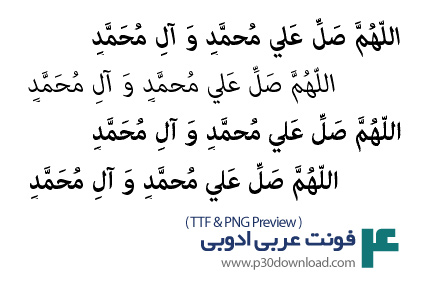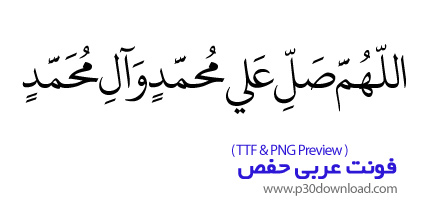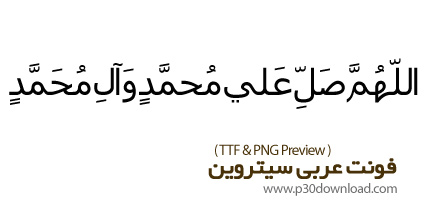
دانلود Meshkal Arabic Font - فونت عربی مشکال: / در این بخش شاهد فونت عربی مشکال می باشید که با فرمت OTF بر روی سایت برای دانلود قرار گرفته است. Meshkal یک فونت نمایشی (Display Font) عربی با طراحی منحصربه‌فرد و مدرن است که از الگوها و ساختارهای هندسی کالیدوسکوپی (Kaleidoscopic Geometries) الهام گرفته شده است. نام این فونت از واژه عربی «مشکال» به معنای کالیدوسکوپ گرفته شده و به‌خوبی بازتاب‌دهنده سبک هندسی و چشم‌نواز آن است. این فونت با ساختاری مستحکم، خطوط ضخیم و لبه‌های تیز طراحی شده و برای پروژه‌هایی که نیاز به تایپوگرافی شاخص، مدرن و متفاوت دارند، گزینه‌ای ایده‌آل محسوب می‌شود. طراحی خاص Meshkal باعث می‌شود در عناوین، پوسترها، برندینگ و پروژه‌های گرافیکی جلوه‌ای قدرتمند و متمایز ایجاد کند. اگر به دنبال یک فونت عربی با هویت هندسی، مدرن و متفاوت هستید، Meshkal Arabic Font با الهام از ساختارهای کالیدوسکوپی و طراحی قدرتمند خود می‌تواند انتخابی عالی برای پروژه‌های تایپوگرافی، پوستر، برندینگ و طراحی‌های خلاقانه باشد. ...
دانلود Bree Arabic 7 Styles Font Family - فونت عربی و انگلیسی بر با 7 استایل مختلف: / در این بخش شاهد فونت عربی و انگلیسی بر با 7 استایل مختلف می باشید که با فرمت های OTF و TTF و WOFF و WOFF2 و JPG بر روی سایت برای دانلود قرار گرفته است. Bree Arabic 7 Styles Font Family  یک خانواده فونت عربی/انگلیسی زیبا و حرفه‌ای است که با طراحی نرم، خوانا و مدرن، گزینه‌ای بسیار مناسب برای انواع پروژه‌های گرافیکی، تبلیغاتی، چاپی و دیجیتال به شمار می‌رود. این مجموعه معمولاً شامل  7 استایل مختلف  از فونت Bree Arabic است که به طراحان اجازه می‌دهد در عین حفظ یکپارچگی بصری، از وزن‌ها و حالت‌های متنوع برای تیتر، متن، لوگو، پوستر، رابط کاربری و محتوای تبلیغاتی استفاده کنند. اگر به دنبال فونتی هستید که هم  ظاهر امروزی و حرفه‌ای  داشته باشد و هم در زبان عربی و فارسی از خوانایی خوبی برخوردار باشد، این خانواده فونت می‌تواند انتخابی کاربردی و ارزشمند برای آرشیو طراحی شما باشد. Bree Arabic نسخه عربی/سازگار با اسکریپت عربی از خانواده فونت Bree است که با حفظ روح طراحی اصلی، برای نوشتار عربی و فارسی بهینه‌سازی شده است. فرم حروف در این فونت معمولاً ترکیبی از  نرمی، صمیمیت، شخصیت بصری مدرن و خوانایی بالا  است؛ به همین دلیل در پروژه‌هایی که هم زیبایی و هم وضوح متن اهمیت دارند، عملکرد بسیار خوبی دارد. ...
دانلود True Arabic Coorporate Clean Sans - فونت عربی و انگلیسی با طراحی مدرن: / این بخش شامل فونت True Arabic Coorporate Clean Sans با پشتیبانی از زبان‌های عربی و انگلیسی می‌باشد که با فرمت‌های OTF، TTF، WOFF و WOFF2 در سایت برای دانلود قرار گرفته است. این فونت مدرن و زیبا، انتخابی ایده‌آل برای طراحی‌های حرفه‌ای و معاصر است و با طراحی تمیز و خوانا، کاربرد گسترده‌ای در پروژه‌های دیجیتال و چاپی دارد. این فونت با ترکیب وضوح، دقت و زیبایی‌شناسی مدرن، یک ابزار حرفه‌ای برای طراحان است و امکان خلق طرح‌های مینیمال، جذاب و خوانا را در هر نوع پروژه فراهم می‌کند. ...
دانلود RAFRAF Font - دانلود فونت عربی و انگلیسی رفراف: / در این بخش شاهد فونت عربی و انگلیسی رفراف می باشید که با فرمت TTF بر روی سایت برای دانلود قرار گرفته است. فونتH RAFRAF یک فونت عربی مدرن و زیباست که با هدف ایجاد خوانایی بالا و طراحی چشم‌نواز ساخته شده است. این فونت صرفاً بر پایه حروف عربی طراحی شده و ممکن است نسخه‌ای ویژه بدون پشتیبانی از حروف لاتین (انگلیسی) باشد. رفراف یک فونت عربی با طراحی معاصر است که به خوبی می‌تواند در طراحی‌های حرفه‌ای مورد استفاده قرار گیرد. ...
دانلود RTL ManGo Arabic Typeface - فونت عربی مانچو: / RTL ManGo Arabic Typeface یک نوع فونت عربی با استفاده از حروف راست به چپ است. این فونت، برای نوشتن و طراحی در زبان عربی و متونی که در جهت راست به چپ نوشته می‌شوند، مناسب است. با استفاده از این نوع فونت، می‌توانید متونی را در استایل و ظاهر عربی منحصر به فردی طراحی و نمایش دهید. RTL ManGo Arabic Typeface انتخابی مناسب برای طراحان گرافیک، نویسندگان عربی و هر کسی است که به دنبال یک فونت عربی با استایل منحصر به فرد می‌باشد که با فرمت های OTF و TTF و JPG بر روی سایت برای دانلود قرار گرفته است. ...
دانلود Lenos Font Family - فونت فارسی، عربی و انگلیسی لینوس: / لنوس (Lenos) نسخه مدرنی از فونت عربی قدیمی "نسخ" است، یک فونت ارگانیک مدرن که سنس و "نسخ" را در یک خانواده قدرتمند با 9 وزن مختلف از نازک تا سیاه و تمام گزینه‌های مورب آن ترکیب می‌کند. لنوس بیش از 50 زبان مختلف را از جمله اردو، فارسی، اسپانیایی، ترکی و غیره، ترکیب می‌کند و همگی قابل استفاده در برنامه‌های دیجیتال و آفلاین هستند. این فونت زیبا با فرمت های OTF و TTF و PNG بر روی سایت برای دانلود قرار گرفته است. ...
دانلود Salford Sans Latin & Arabic Font Family - فونت لاتین و عربی صلفرد سانز: / در این بخش شاهد فونت لاتین و عربی صلفرد سانز می باشید که با فرمت OTF بر روی سایت برای دانلود قرار گرفته است. فونت Salford Sans Latin & Arabic Font Family یک خانواده‌ی تایپوگرافی مدرن و همه‌کاره است که به‌طور حرفه‌ای برای پوشش زبان‌های لاتین و عربی طراحی شده است. این خانواده فونت برای طراحانی ساخته شده که به دنبال هماهنگی کامل میان متون انگلیسی و عربی در پروژه‌های چندزبانه هستند. سبک‌های لاتین و عربی در این خانواده فونت به‌صورت کاملاً هماهنگ طراحی شده‌اند تا انسجام بصری در پروژه‌های چندزبانه ایجاد کنند. این فونت با تمرکز بر خوانایی و سادگی، مناسب برای استفاده در وب‌سایت‌ها، اپلیکیشن‌ها، تبلیغات، نشریات، و طراحی برندینگ است. طراحی بر پایه‌ی اشکال هندسی نرم و متوازن انجام شده که حس مدرن، مینیمال و حرفه‌ای به پروژه‌ها می‌دهد. ...
دانلود فونت عربی امیری - Amiri
شما کاربران گرامی شاهد فونت عربی امیری با فرمت TTF هستید. طراحان وب سایت و گرافیست های خلاق می توانند از این فونت زیبا در طراحی پروژه های مذهبی، اسلامی خود استفاده کنند.
دانلود فونت عربی کوفی جراف - Kufigraph
شما کاربران گرامی شاهد فونت عربی کوفی جراف با فرمت TTF هستید. طراحان وب سایت و گرافیست های خلاق می توانند از این فونت زیبا در طراحی پروژه های مذهبی، اسلامی خود استفاده کنند.